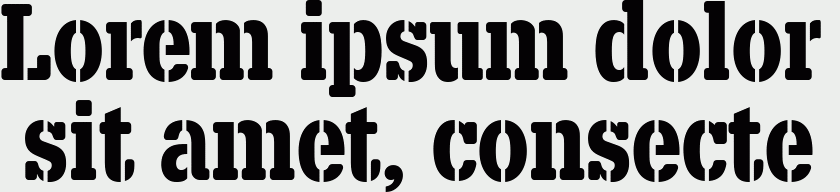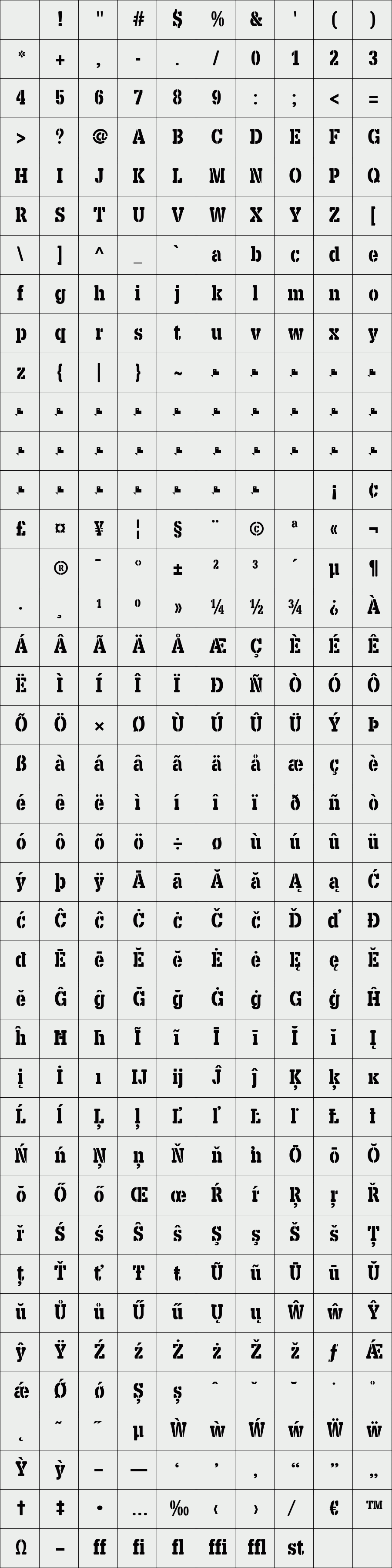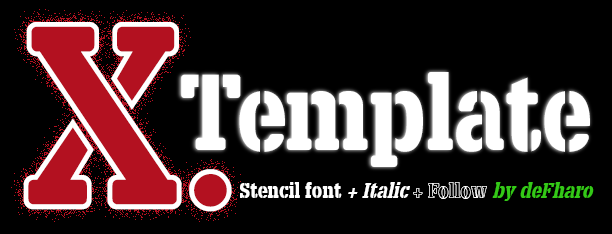
X.Template
X.Template es una tipografía negra y condensada, de gruesa serífas redondeadas, con estilo stencil o militar.
La familia X.Template la componen 3 fuentes: Regular, Itálica y una versión Outline (Hollow).